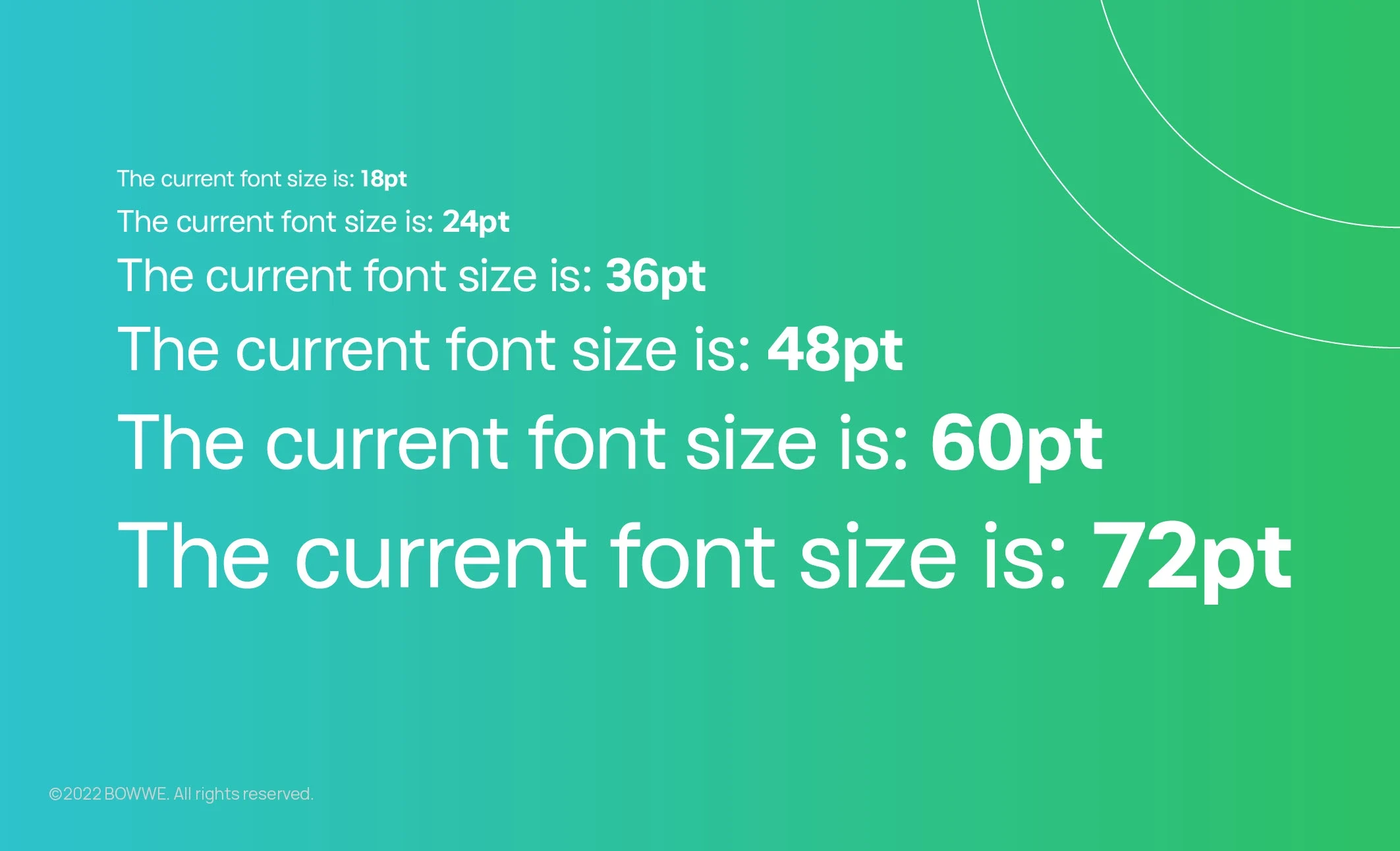
Una tipografia ben congegnata e ben scelta è la chiave per ottenere un sito web esteticamente gradevole e, soprattutto, facilmente leggibile. Ma sai come rendere il testo del sito web chiaro e coerente con l'identità del tuo brand?
Non preoccuparti. Ho raccolto le 8 regole tipografiche più cruciali che renderanno l'intero processo di creazione della tipografia perfetta per il tuo sito web facile ed efficace. Assicurati di seguire tutte le regole e sarai ricompensato con un sistema di tipografia trasparente che renderà il tuo progetto professionale e migliorerà la sua UX.
8 principi di tipografia da seguire
1. Scegli il carattere giusto
La cosa più importante è che la tua tipografia dovrebbe riflettere la vera natura del tuo settore. Pertanto, la scelta della giusta tipografia del sito Web non può essere casuale. Solo perché un font è popolare e ti piace non significa che sarà appropriato per il tuo marchio. Presta attenzione a ciò che comunica il carattere e se corrisponde allo stile del tuo marchio.
Presta attenzione a ciò che comunica il carattere e se corrisponde allo stile del tuo marchio. Se gestisci un negozio per bambini, non utilizzerai caratteri aziendali semplici ed eleganti e viceversa. Abbina sempre i caratteri alla comunicazione del tuo marchio per essere coerente con esso.
2. Seleziona la dimensione del carattere
La dimensione del carattere sulla pagina è importante! Se scegli un carattere che non sia né troppo piccolo né troppo grande, renderai la lettura molto più semplice per i tuoi utenti. Un'unità speciale utilizzata dai tipografi per descrivere i caratteri è "pt" o "point".
La gamma preferita di dimensioni dei caratteri standard per i siti Web è compresa tra 14 e 25 pt. I caratteri più grandi possono essere riservati per i titoli - 20pt e oltre , e per il testo normale, l'intervallo migliore è 14-18pt.
Indipendentemente dalla dimensione del carattere che scegli, assicurati che la dimensione del carattere:
a) rende leggibile il testo - la dimensione del carattere di 12pt o inferiore può ostacolare notevolmente la leggibilità;
b) corrisponde al carattere tipografico - ad esempio, per il suo carattere di sistema Roboto Google consiglia un minimo di 16 pt. D'altra parte, San Francisco - il carattere utilizzato, tra gli altri, nei dispositivi Apple, dovrebbe avere una dimensione di almeno 18pt;
c) rispecchia lo scopo del sito web - se la pagina non è dominata dal testo ma dal design, puoi utilizzare un carattere più piccolo. Anche nel caso di pagine interattive che incoraggiano l'utente a cliccare ad ogni passaggio, questa soluzione può essere permessa. Se invece hai a che fare con un sito web dove il testo domina, e il compito principale dell'utente è la lettura (es. area blog, portale informativo) - è meglio scegliere un font leggermente più grande.
Come scegliere la dimensione dell'intestazione?
Hai deciso la dimensione del carattere del corpo del testo ma non sai come mantenere la dimensione dei titoli in proporzione al resto del contenuto? Esistono diverse best practice per questo:
a) L'intestazione H1 dovrebbe essere il 300% della dimensione del carattere utilizzata nel corpo del testo. Ad esempio, se il tuo sito web utilizza un font 18pt per il corpo del testo, la dimensione ottimale per le intestazioni è 54pt.
b) L'intestazione H2 dovrebbe essere il 200% della dimensione del carattere del corpo del testo. In questo caso, con una dimensione del carattere di base di 18pt, l'intestazione H2 ideale sarebbe 36pt.
⚡ BOWWE Tip:
Per le intestazioni successive è possibile diminuire gradualmente la percentuale; ad esempio, per l'intestazione H4, puoi moltiplicare la dimensione del carattere principale del 130-150%.
Caratteri nella versione mobile
Quando si sceglie la dimensione del carattere, è necessario rispondere alla domanda su quali dispositivi verrà visualizzato il testo. La dimensione del carattere apparirà diversa sui monitor dei laptop rispetto ai dispositivi mobili. Se preferisci concentrarti sull'aspetto del sito web sui dispositivi mobili, ricorda queste due regole importanti:
a) Sugli schermi degli smartphone, un carattere grande non starà bene,
b) Le intestazioni non devono occupare più di due righe.
Pertanto, quando si progetta un sito Web mobile, vale la pena controllare l'aspetto del testo e assicurarsi che il carattere sia troppo grande.